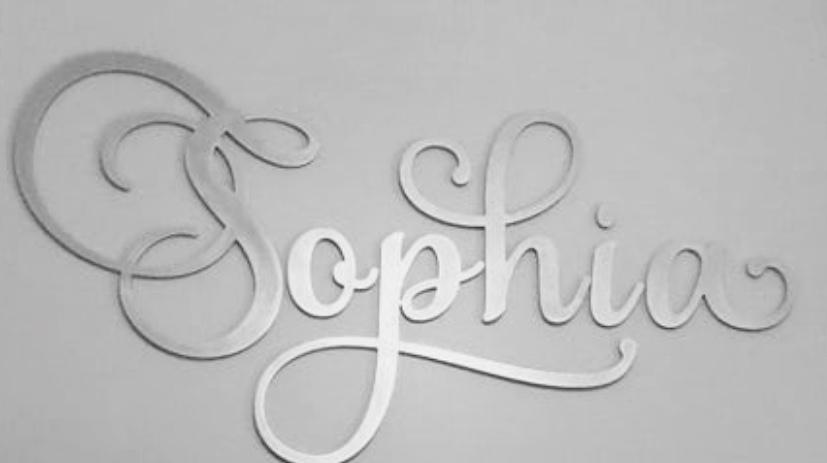
Hallo, ich suche diese Schriftart, finde sie nicht. Habe auch in diversen Schriftfindungsprogrammen nachgeschaut. Dieses Foto hat Woodonplex über Instagram veröffentlicht, daher dieser Screenshot.
Vielen Dank für den Tipp. Wenn ich das kleine h anschaue ähnelt es mehr Samantha italic. Woher das S kommt ist eine gute Frage..
Und das S kann man das auch finden? Suche auch schon. Lieben Dank das ist echt eine Hilfe:)
Zumal das Ende des Swooshes am S auch nicht der Formensprache der anderen Swooshes entspricht – der Tropfen fehlt.
Vielleicht aus einer anderen Schrift (von Frau Worthington)?